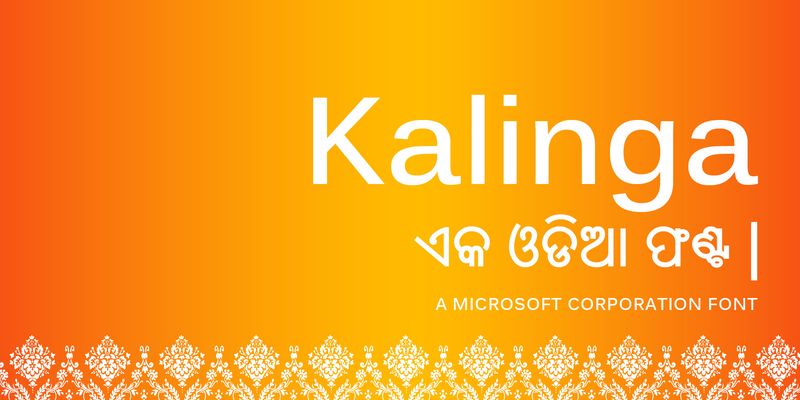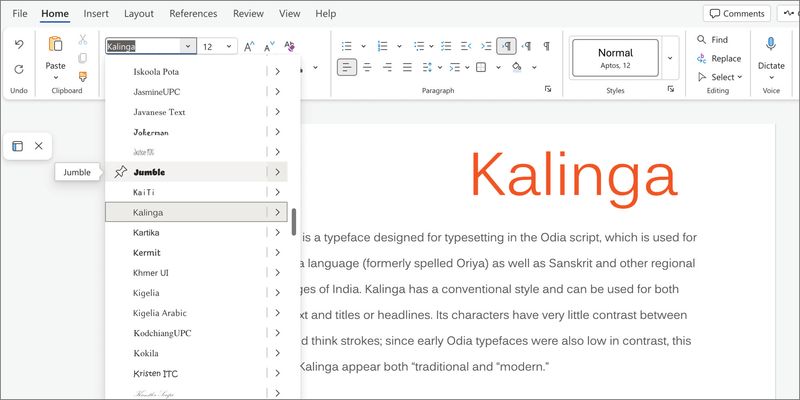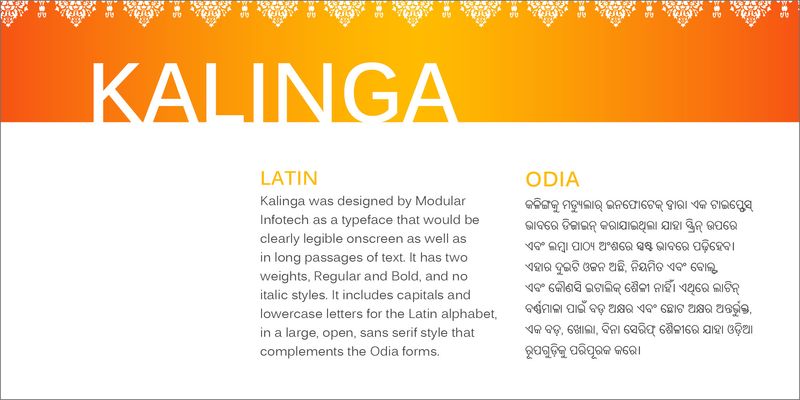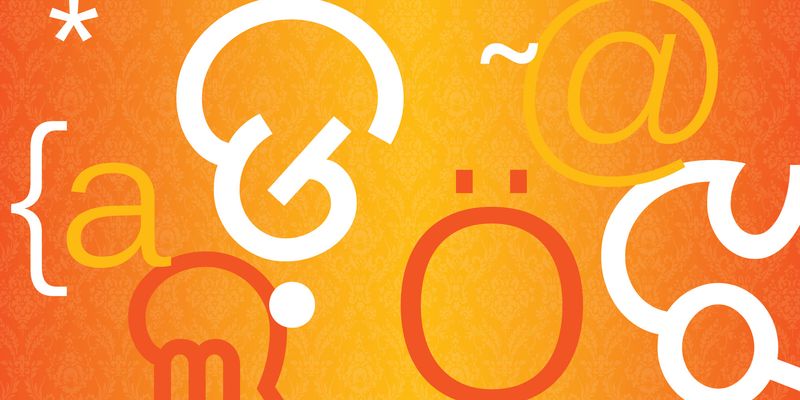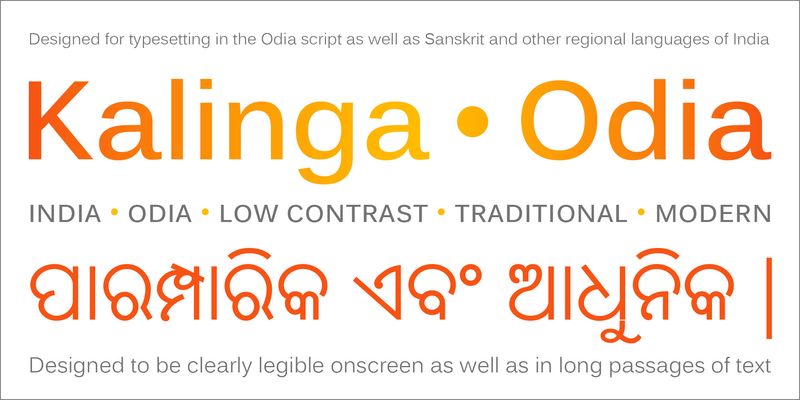
„Kalinga“ ist eine Schrift für die indoarische Sprache Odia (bis 2011 Oryia genannt) und das entsprechende Schriftsystem. Die Sprache wird hauptsächlich im indischen Bundesstaat Odisha (bis 2011 Orissa) verwendet und ist nach dem antiken Königreich Kalinga benannt, dessen geografisches Gebiet weitgehend mit dem heutigen Odisha übereinstimmt. Die Kalinga unterstützt auch andere indische Regionalsprachen sowie Sanskrit und eignet sich aufgrund ihres neutralen Stils für Fließtext, Titel und Überschriften. Wie bei den Vorgängern dieser Schrift ist der Kontrast zwischen dicken und dünnen Strichen in den Buchstaben sehr gering. Dadurch wirkt die Kalinga traditionell und modern zugleich.
Bei der Gestaltung der Kalinga durch Modular Infotech stand die Lesbarkeit der Schrift sowohl am Bildschirm als auch in längeren Fließtexten im Vordergrund. Sie ist in den zwei Schriftstärken, Regular und Bold, erhältlich, verfügt aber über keine Kursivschnitte. Neben den Formen des Odia-Schriftsystems bietet die Kalinga auch Versalien und Minuskeln des lateinischen Schriftsystems, mit einem großen, offenen, serifenlosen Stil.